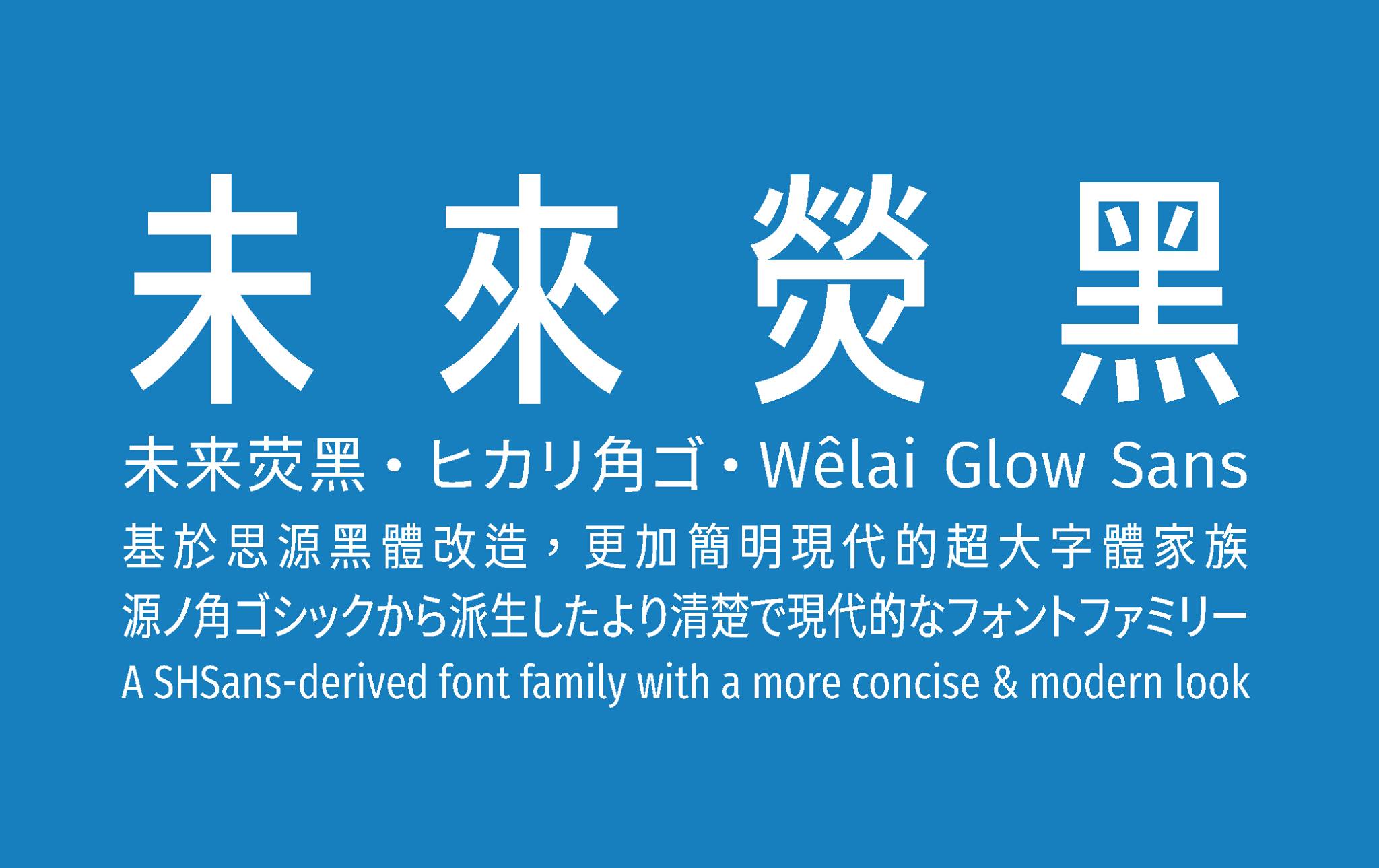
未来荧黑\未來熒黑\ヒカリ角ゴ\Wêlai Glow Sans
未来荧黑是一个基于思源黑体、Fira Sans和Raleway的开源字体项目,支持简体中文、繁体中文与日文;思源黑体的7字重被扩展为9字重,并提供了宽度系列,全家族共44款字体。
相比于思源黑体,未来荧黑的造型更加简明现代,版面效果清新轻快。未来荧黑的中宫与字面更加收敛,重心在字重之间经过了重新配置;笔画细节上处理得更加干练,简洁而平直化。您可以下载样张来预览未来荧黑的设计。
未来荧黑的实现介于参数化与轮廓滤镜,使用了图像处理算法对字形建模。字体的制作并没有借助字体设计软件,而是用一个Web实现的可视化调参工具来确定字体参数。
- Q: 这是可变字体吗?
- A: 不是。未来荧黑是通过在思源黑体上形变来改变字形形态、拓展家族的,思源黑体没有发布可变版本,我们也无从恢复其母版数据。但是不排除在未来有封装成有宽度轴的可变字体的可能性。你可以玩一玩我们的demo,来更加直观地看到形变是如何实现的。
- Q: 支持韩文吗?
- A: 不支持。以后的版本可能会提供韩文支持。
- Q: 曲线质量似乎不高啊?
- A: 因为形变算法并不完美。未来荧黑的目标仅仅是提供一个开源替代品,来弥补免费可商用中文字体的一个缺口,提供可用性上的便利。当然,提升输出曲线质量仍然是本项目的一个技术指标。
- Q: 为什么有的思源黑体支持的字在未来荧黑不支持?
- A: 这些字符在宽度系列的处理上存在着很大难度,因此被暂时剔除了,例如“Enclosed CJK Letters And Months”。此外,暂时不支持
ccmp,并不计划支持中日韩语言的locl特性。